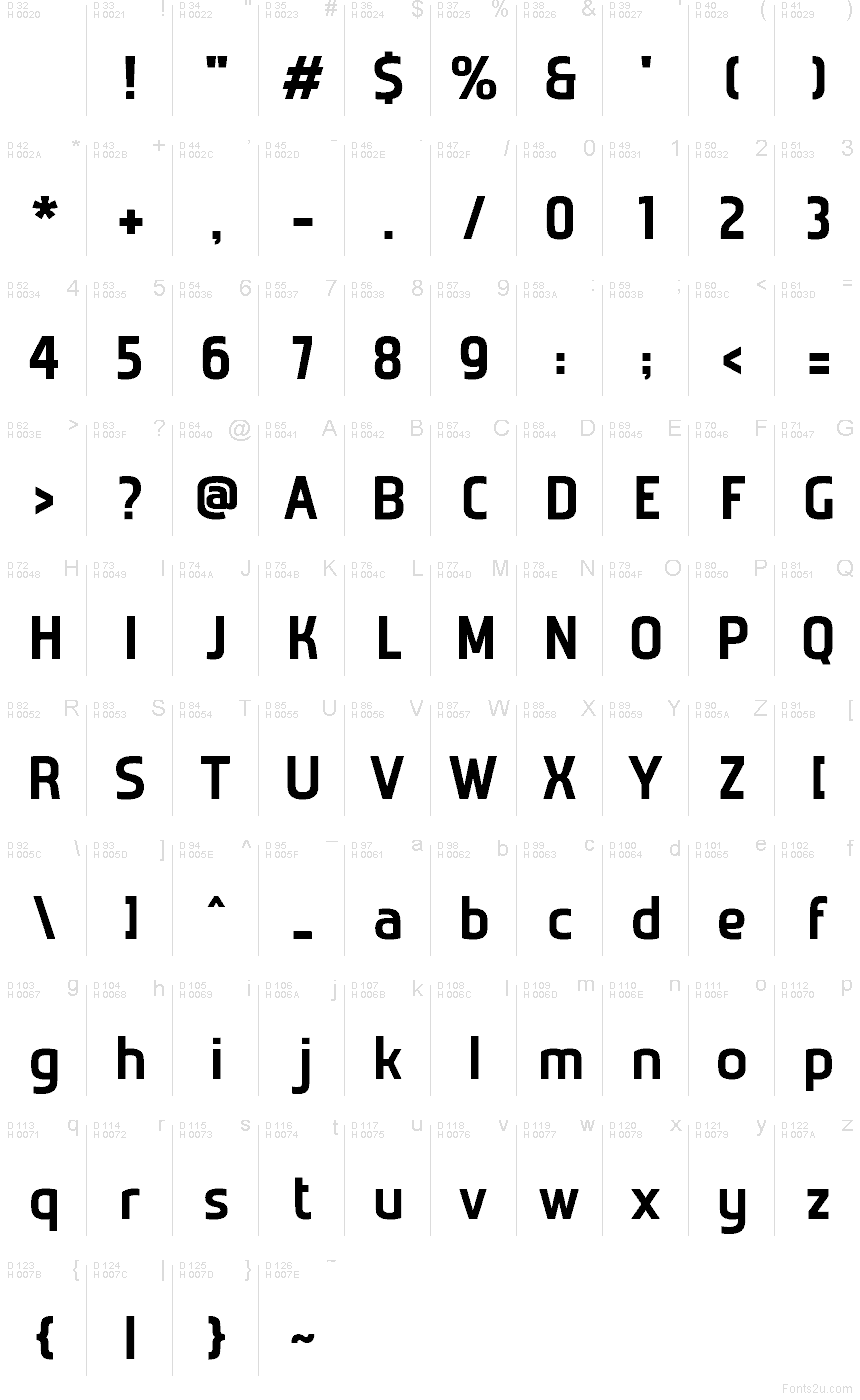
Emirates Essentials Semi Bold od Glyphminds Studios je bezplatné, polotučné bezpätkové písmo s čistým, moderným tónom, ktoré pôsobí ako stvorené pre súčasný branding. Písmená spájajú široké, otvorené krivky s jednoduchými, pevnými ťahmi, vďaka čomu písmo pôsobí priamočiaro a urbánne, nie neutrálne či korporátne.
Prirodzene zapadá do systémov značiek, grafiky aplikácií, orientačných systémov, redakčných nadpisov, obalov a titulných kartičiek, kde bezplatné písmo potrebuje priamy hlas s trochou hrejivosti. Zvlášť dobre sa hodí na krátke titulky a obalové texty, pretože zaoblené tvary udržujú priateľský charakter, zatiaľ čo jeho hrúbka dodáva slovám dostatočnú výraznosť.